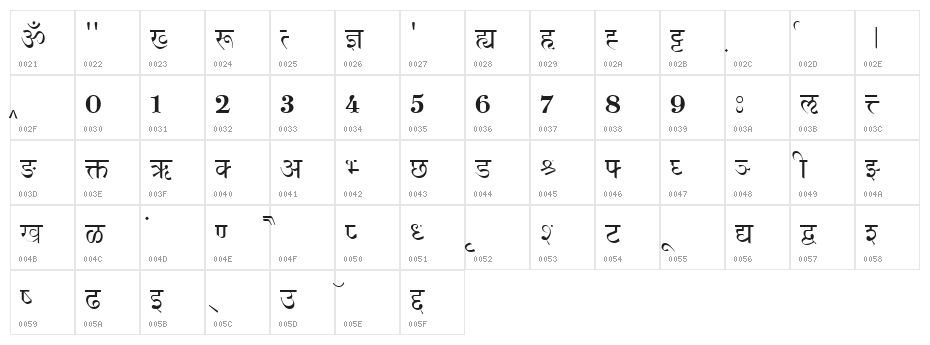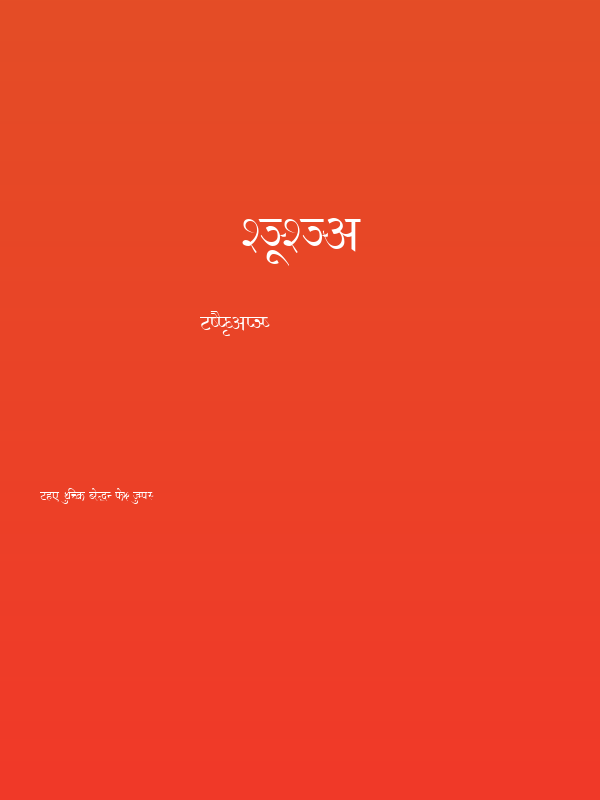
Shusha Font
| Caso d'uso | Headlines, Body text, Cultural publications |
| Progetti proposti | Ideal for use in traditional Indian publications, cultural event posters, and educational materials. |